虽然我们常说设计要简洁,但更多设计作品的问题主要是太单调、太单薄,这会导致设计不够美观和精致,那么如何才能使设计变得丰富起来呢?下面让我们一起来揭秘。
1. 丰富标题
标题是非常重要的,所以它在设计中也常常占据不小的空间,如果在标题的设计上花点心思,也能起到丰富画面的效果。
比如可以给标题做字体设计,将文字的笔画变形,或者融入与其相关的图片图形元素。
比如就像下面这款逐浪圆体,这款字体是以一款POP风格的卡通字体为原形,字体间嵌入了可爱的卡通图案,是非常可爱的一款字体。
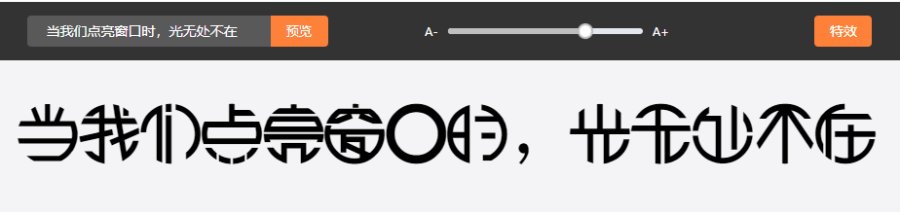
2.丰富次要文字
在一件完整的平面设计作品中,通常除了标题和正文外,还会有第三种文字,比如注解或者是装饰性的文字,这类文字的字号通常会比较小,丰富这些文字可以使其装饰效果更加,也能使画面更精致。
字体设计在设计中拥有着不可被替代的位置,字体设计是设计标志,是设计的眼睛,是设计传播表达的语言。所以,文字设计在设计中有着举足轻重的重要性。